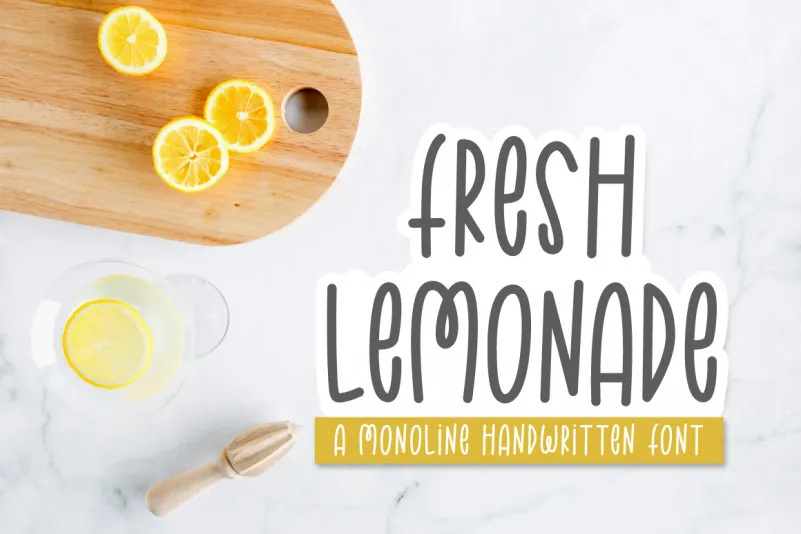
Fresh Lemonade Font – Download Grátis
A Fresh Lemonade Font é uma seleção perfeita para quem procura uma fonte com estilo único que se destaca por sua simplicidade de leitura. Esta fonte monoline permite criar desenhos elegantes e modernos, adequada tanto para textos quanto para elementos gráficos como logotipos ou designs de roupas infantis. Suas linhas retas e diretas fazem com que ela seja ideal para mensagens inspiradoras e design divertido, como t-shirts ou anúncios criativos para a web. A Fresh Lemonade Font é uma escolha perfeita para designers buscando um recurso gráfico atemporal e versátil, que se destaca em qualquer ambiente de projetos. Para usuários de blogs de design, esta fonte oferece uma maneira única de personalizar seus posts com um toque alegre e criativo. Seja você designer de moda ou especialista em marketing online, essa fonte pode transformar sua apresentação de trabalho. Com seu estilo único e facilidade de leitura, Fresh Lemonade é o tipo certo para deixar sua marca mais distintiva em qualquer projeto gráfico.